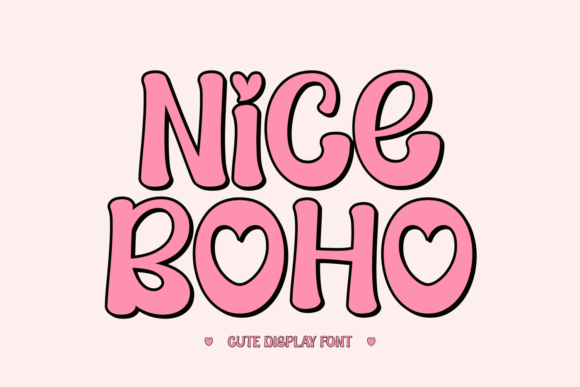
Nice Boho
Nice Boho – A Review que Todo Designer Precisa Ler
Se você está em busca de fontes que transmitam boho chic com um toque contemporâneo, Nice Boho da coleção 7ntypes Display é a escolha ideal. Essa fonte combina a nostalgia dos retro e vintage com a energia vibrante dos estilos groovy e chunky, criando um visual que se destaca em qualquer projeto — seja um t‑shirt, um banner de branding ou um post de social media.
- Design versátil: Nice Boho funciona perfeitamente em craft, sublimation e projetos Cricut, facilitando a criação de adesivos, camisetas e itens de decoração.
- Legibilidade elegante: Apesar do estilo descontraído, a fonte mantém a clareza típica das serif fonts, garantindo fácil leitura em tamanhos pequenos.
- Estação do ano: Seus traços fluídos capturam a vibração do summer e spring, mas também se adaptam ao clima autumn e winter, tornando-a ideal para campanhas sazonais.
- Aplicação de marca: Ideal para fashion, trend e playful branding, Nice Boho traz personalidade sem perder a sofisticação.
Em resumo, Nice Boho não é apenas mais uma fonte “boho”. Ela oferece elegância, originalidade e alta performance para designers que desejam criar peças marcantes e memoráveis. Se o seu objetivo é atrair atenção instantânea e transmitir a vibe descontraída do estilo boho, esta fonte merece um lugar de destaque no seu arsenal criativo.